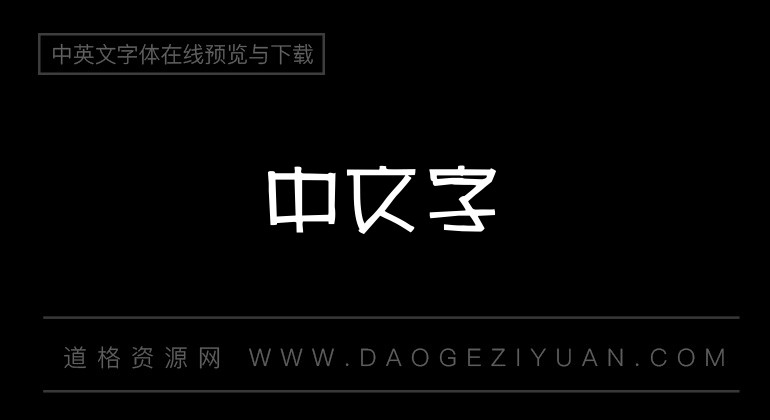
雅坊美工02
? 雅坊美工02字体是一款简约、大气、清新、时尚的汉字字体,它采用了自然舒适的笔画,拥有清晰的线条,让字体看起来更加精致,更有质感。它具有清晰、精细、流畅的字形,可以让文字更加清晰、精致、时尚,适用于各种印刷、网页设计、平面设计等场景。
雅坊美工02是一款非常不错的手写艺术字体,具有很好的视觉感,适合于文化类的宣传设计、商业类品牌的广告和产品包装设计以及个性化文字排版等较多场景。
雅坊美工02字符映射图